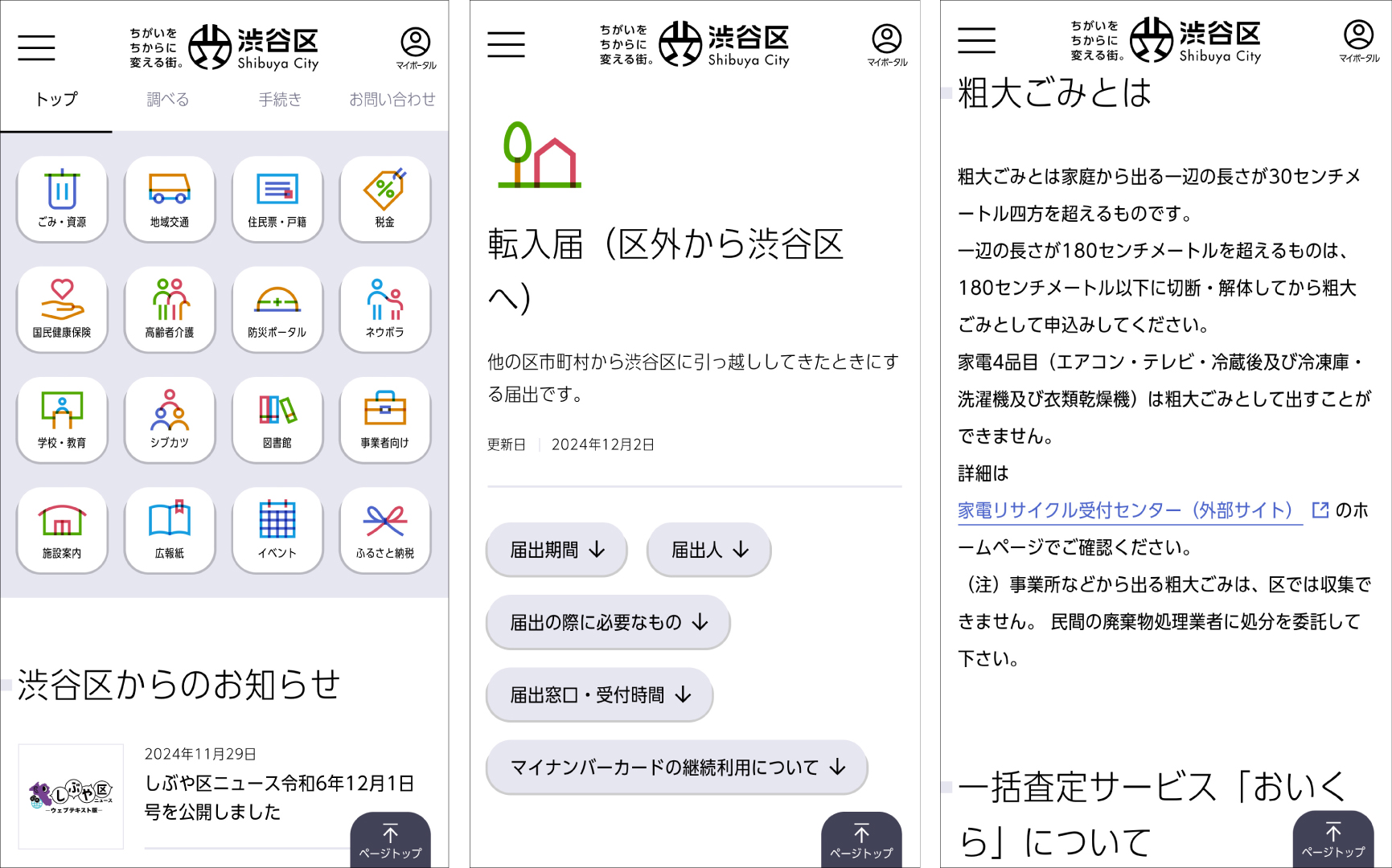
リニューアルを実施した渋谷区公式WebサイトにモリサワのUDフォントが採用されました〜Webサイトを制作する約7割のクリエイターが「UDフォント」を使用するという調査結果も〜
株式会社モリサワ(以下モリサワ)のユニバーサルデザインフォント(以下UDフォント)が、リニューアルを実施した東京都渋谷区の公式Webサイト「渋谷区ポータル」で採用されました。モリサワが2024年に実施したUDフォントに関する調査によると、Webサイトを制作するクリエイターの68%が「UDフォントを使用する」と回答しており、UDフォントの活用が広がっています。さまざまなバックグラウンドを持つ方が閲覧する自治体Webサイトにおいても、誰一人取り残さない情報発信が求められます。
渋谷区では、早くからDX化に注力するとともに、文字の見やすさ、読みやすさに徹底してこだわっていて、リニューアル前の2016年からモリサワのUDフォントを採用いただいています。リニューアルにおいて、渋谷区では「スマートフォンユーザーの増加」を意識したサイト設計を行いました。スマートフォンはPCと違って文字数が少なく表示されることから、「UD新ゴ コンデンス90」という横幅が狭く設計されたコンデンス書体を採用いただき、読みやすさと文字数を両立しています。同サイトは、コンセプトやデザイン性が評価され、グッドデザイン賞(主催 公益財団法人日本デザイン振興会)を受賞するとともに「グッドデザイン・ベスト100」にも選出されています。
UDフォントに関する調査結果について
モリサワでは2024年11〜12月にアンケート調査を実施。その結果によると、UDフォントを選ぶ際に意識するポイントとして、「障害の有無や年齢に関わらず、より多くの方が読みやすいフォントを選びたい」という方が半数を占め、幅広いターゲット層への情報発信の際にUDフォントが多く選ばれていることが分かりました。
また、Webサイトを制作するクリエイターの68%が「UDフォントを使用する」と回答するなど、UDフォントの活用が広がっています。
モリサワのUDフォントについて
モリサワのUDフォントは、「文字のかたちがわかりやすいこと」「文章が読みやすいこと」「読み間違えにくいこと」をコンセプトに開発されています。具体的には、濁点や半濁点を大きくして、区別をつけやすくしているほか、シルエットの似た文字を判別しやすくするために、はなれを明確にするなどの工夫をしています。第三者機関と共同で可視性・可読性に関する比較研究報告も実施しています。